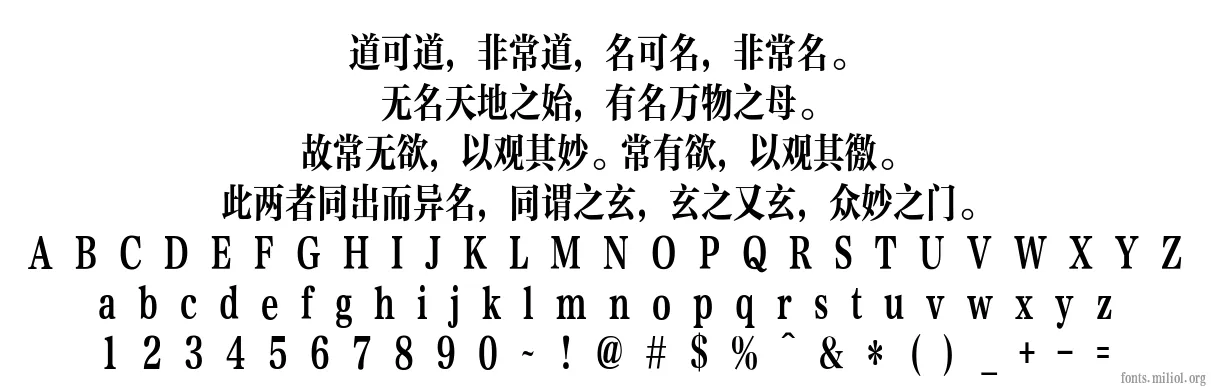
**方正粗雅宋长_GBK字体简介**
方正粗雅宋长_GBK(FZYaSong-BN-GBK)是一款兼具传统宋体韵味与现代设计美感的字体,隶属于方正字库的经典系列。其笔画粗壮有力,结构舒展修长,在标题、广告、海报等大字号场景中表现尤为突出。GBK编码支持繁简中文及日韩字符,适用性广泛。
该字体以雅宋为基础,通过加粗和纵向延伸的处理,既保留了宋体的端庄典雅,又增添了视觉冲击力,适合文化宣传、品牌包装等需要强调文化底蕴的领域。文件命名中的“FZCYSCK--GBK1-0”为其内部版本标识,用户需通过正规渠道获取授权以确保合规使用。
作为一款专业字体,方正粗雅宋长_GBK在印刷与数字媒体中均能展现独特的美学效果,是设计师提升作品质感的优质选择。